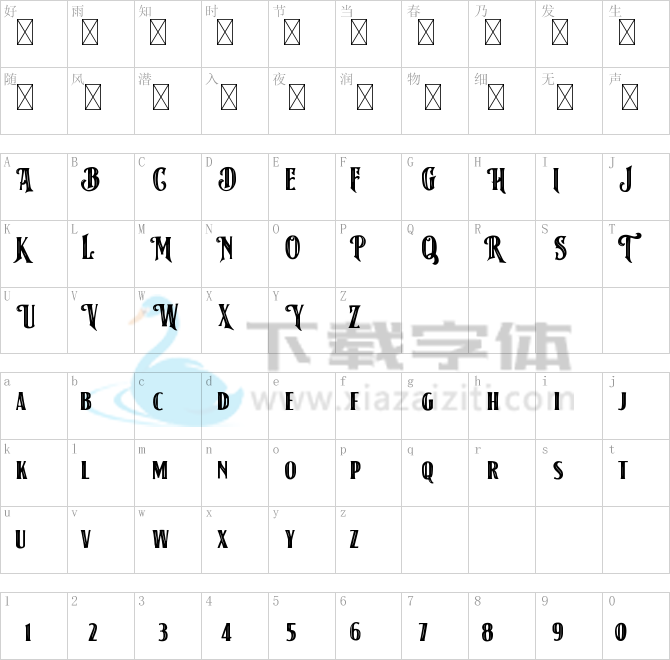
American Label Strip.ttf字体下载,这款字体结构工整、笔画清晰,兼顾美观与易读性,适用于标题、正文、海报、包装、LOGO 等多种场景。字形优雅稳定,风格百搭耐看,适配日常排版与创意设计,让文字呈现更舒适、更具质感。American Label Strip.ttf字体下载一笔一画,皆是细节,以均衡的比例、流畅的线条打造舒适视觉体验,字形端正大气,风格简约现代。无论是商业设计、品牌宣传还是日常排版,都能轻松驾驭,让文字更有格调与力量。American Label Strip.ttf字体下载字体下载。